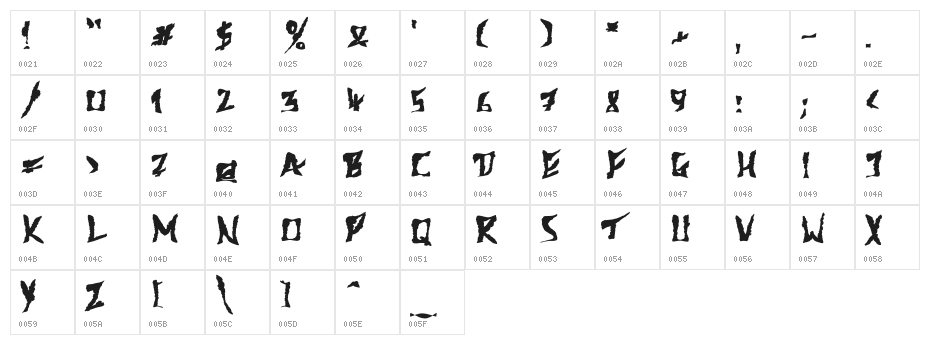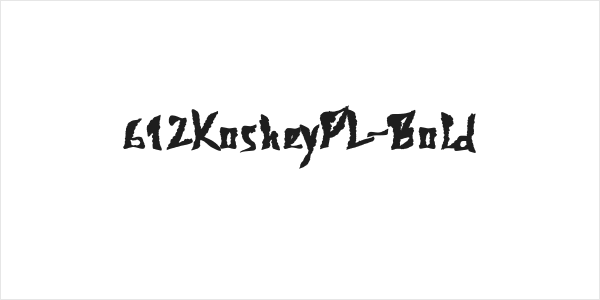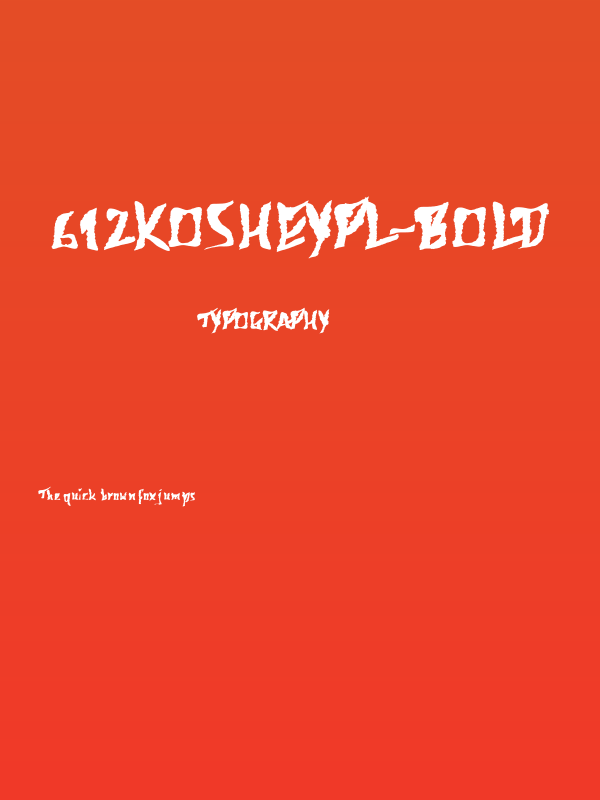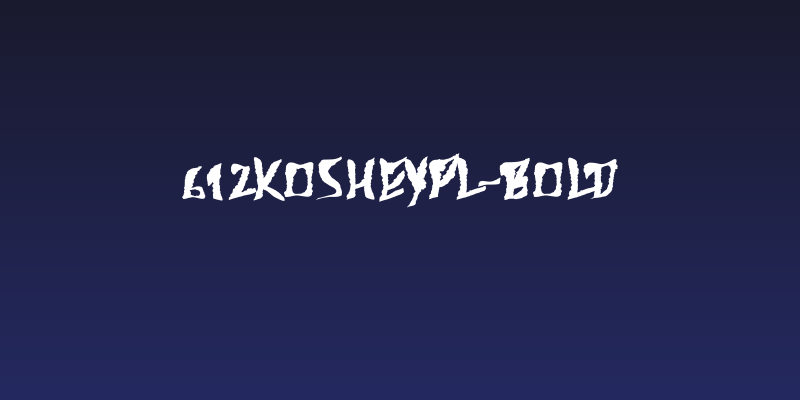
612KosheyPL-Bold Font
| Progetti proposti | Ideal for use in edgy branding, album covers, street art-inspired designs, and posters that require a bold statement. |